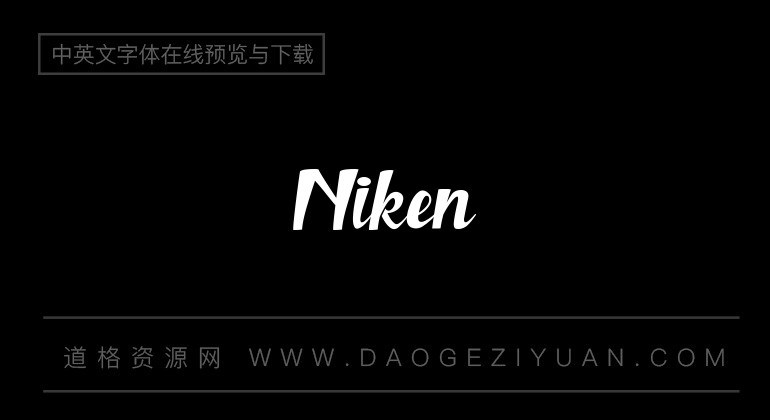
Niken 字体是一款由丹麦设计师 Mads Freund Brunse 创作的字体,它是一款折行字体,特点是字体设计简洁而又大胆,具有现代风格,可以用于多种类型的设计,如海报、广告、标识、品牌等。它具有良好的可读性,并且可以在多种尺寸和颜色上进行调整,可以帮助您设计出独特且有吸引力的作品。内容介绍
Niken是一款非常不错的手写艺术字体,具有很好的视觉感,适合于文化类的宣传设计、商业类品牌的广告和产品包装设计以及个性化文字排版等较多场景。